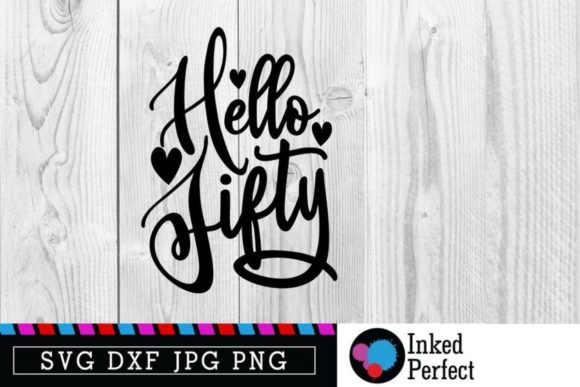
Hello Fifty Hand-Lettered Font
找到合适的设计元素可能具有挑战性,但 Hello Fifty Hand-Lettered Font 提供了一系列出色的藏品,可瞬间提升您的作品质量。
精心制作的 Hello Fifty Hand-Lettered Font 提供干净的矢量、流畅的排版以及让您安心的商业许可证。
无论您是创建 POD(按需打印)产品、婚礼邀请函还是社交媒体图形,Hello Fifty Hand-Lettered Font 都是理想的选择。